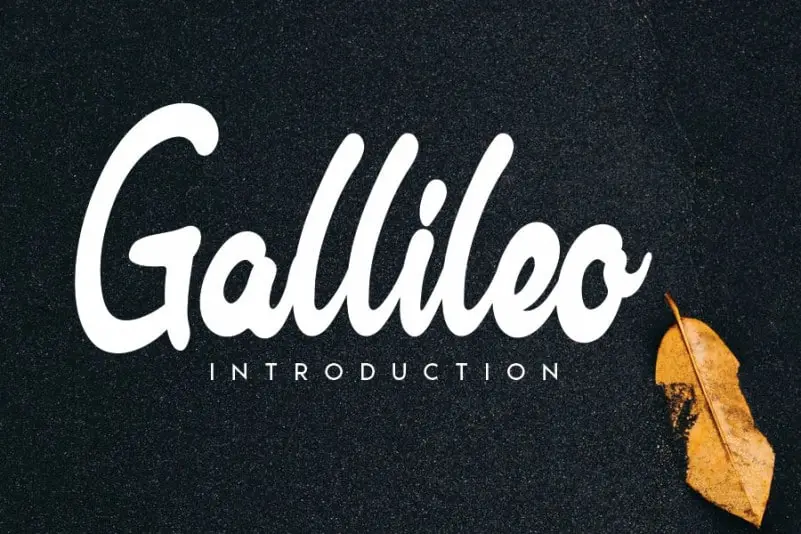
Gallileo Handwritten Font – Download Grátis
A Gallileo Handwritten Font é uma deliciosa escrita cursiva com um ar encantadormente amigável. Perfeita para quem procura inspiração no mundo digital, seja para postagens na sua página de Instagram ou para adicionar uma pitada delicada à seus projetos DIY, esta fonte transformará ideias criativas em verdadeiras obras de arte. Seja você um designer gráfico, artesão ou simplesmente alguém que busca dar um toque pessoal a suas criações digitais, Gallileo é a escolha perfeita para aqueles que valorizam uma escrita elegante e descontraída.